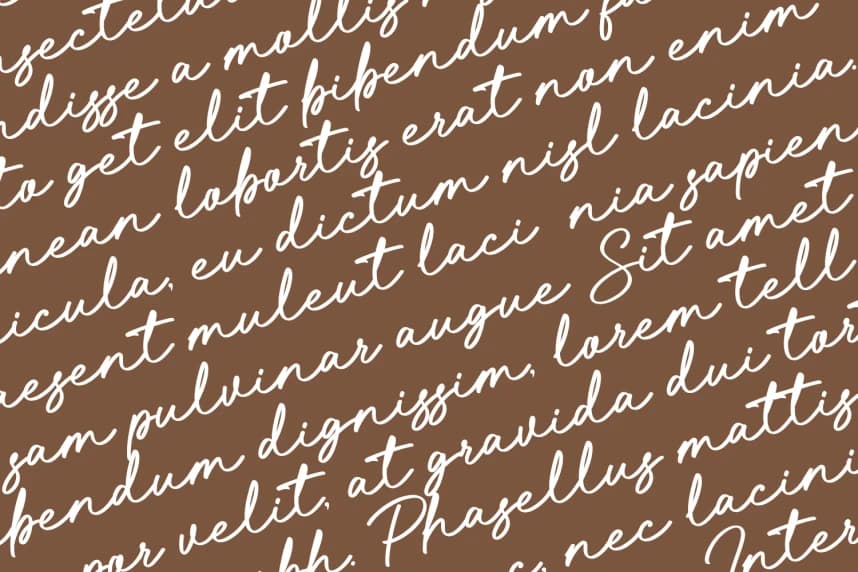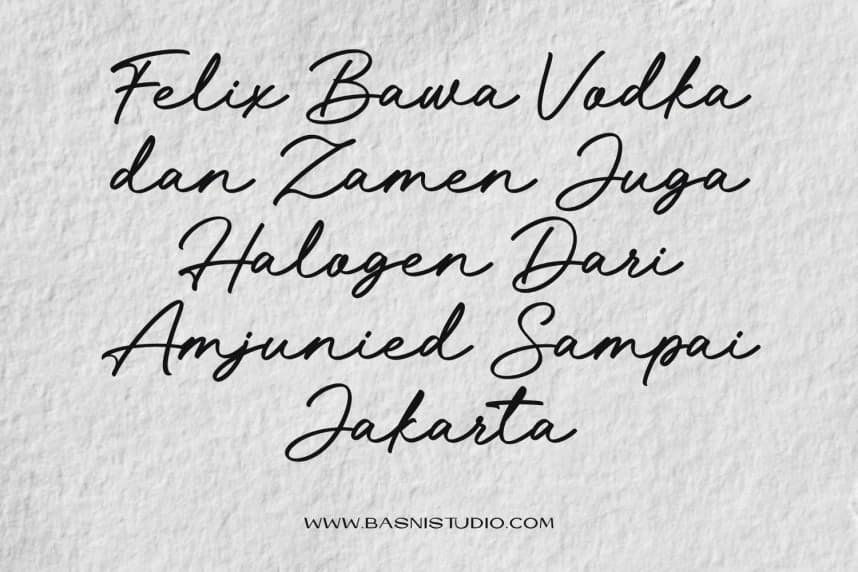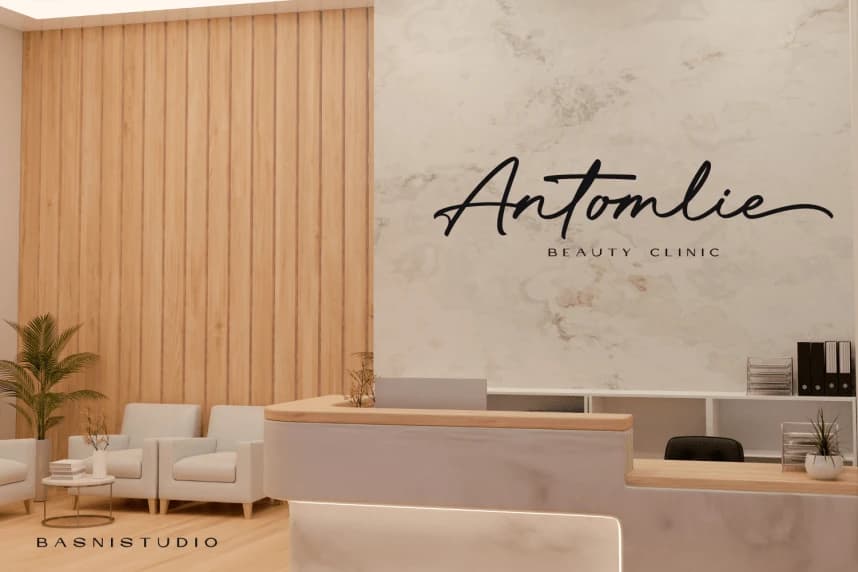
Sederhana – Kalın El Yazısı Yazı Tipi
Sederhana Bold el yazısı fontu, gerçek fırça ile tasarlanmış; doğal ve rahat bir dokunuş için branding ve social media'dan davetiyeler ve ambalajlara kadar her şey.
Sederhana Bold el yazısı fontu, otantik fırça ile hazırlanmış doğal ve sade bir dokunuş için; markalaşmadan sosyal medyaya, davetiyelerden ambalaja kadar her şey için.
Sederhana – Bold Handwriting